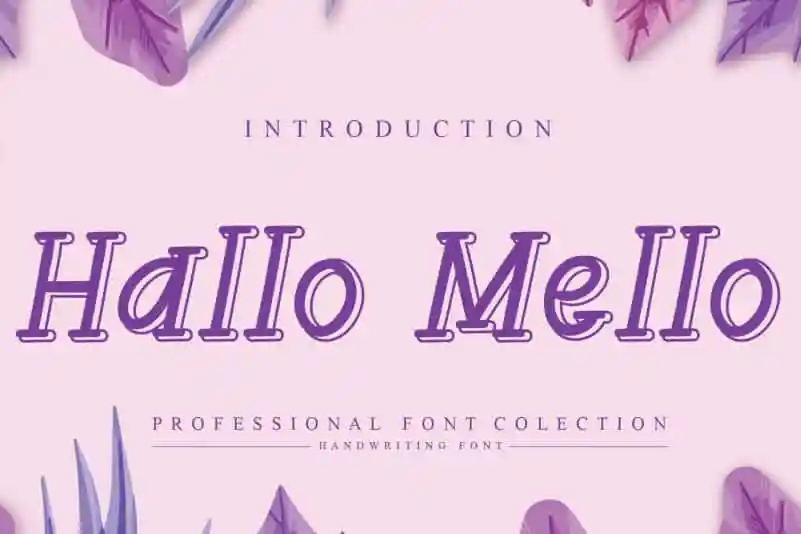
Hallo Mello Display Font – Download Grátis
A fonte ‘Hallo Mello Display Font’ oferece uma experiência visual sofisticada que vai encantar os designers digitais. Seu estilo único e elegante a torna perfeita para criar identidades de marca memoráveis, logos criativos e cartões de boas-vindas incrivelmente bonitos. Não importa o projeto em que você esteja trabalhando, esta fonte atua como uma mãozinha adicional, ajudando a transformar ideias em arte visual impactante. Com seu designer responsável, andikastudio, garantindo uma experiência de uso fluida e fácil customização, ‘Hallo Mello Display Font’ é definitivamente um investimento valioso para qualquer estilista gráfico que busca novas maneiras inovadoras de expressar sua visão pessoal através da tipografia.